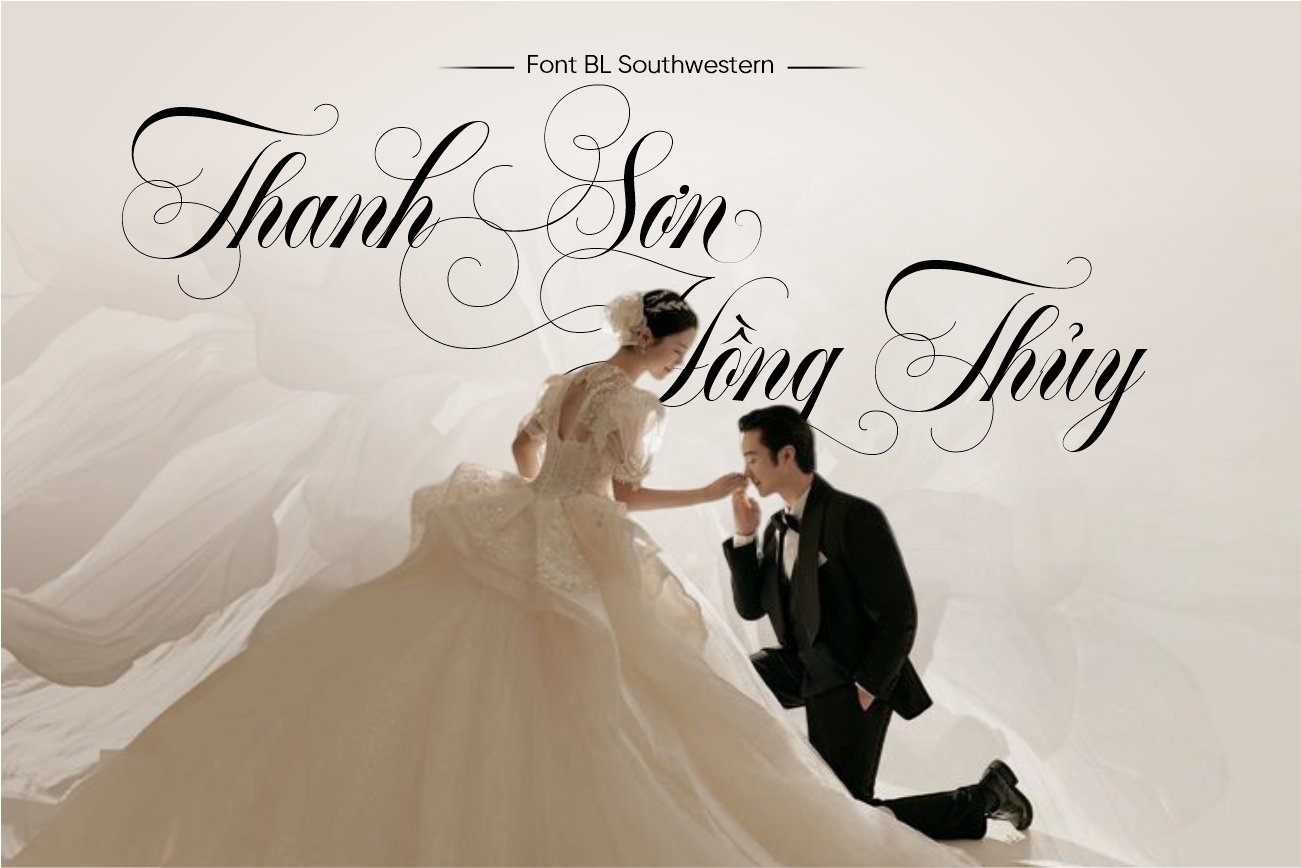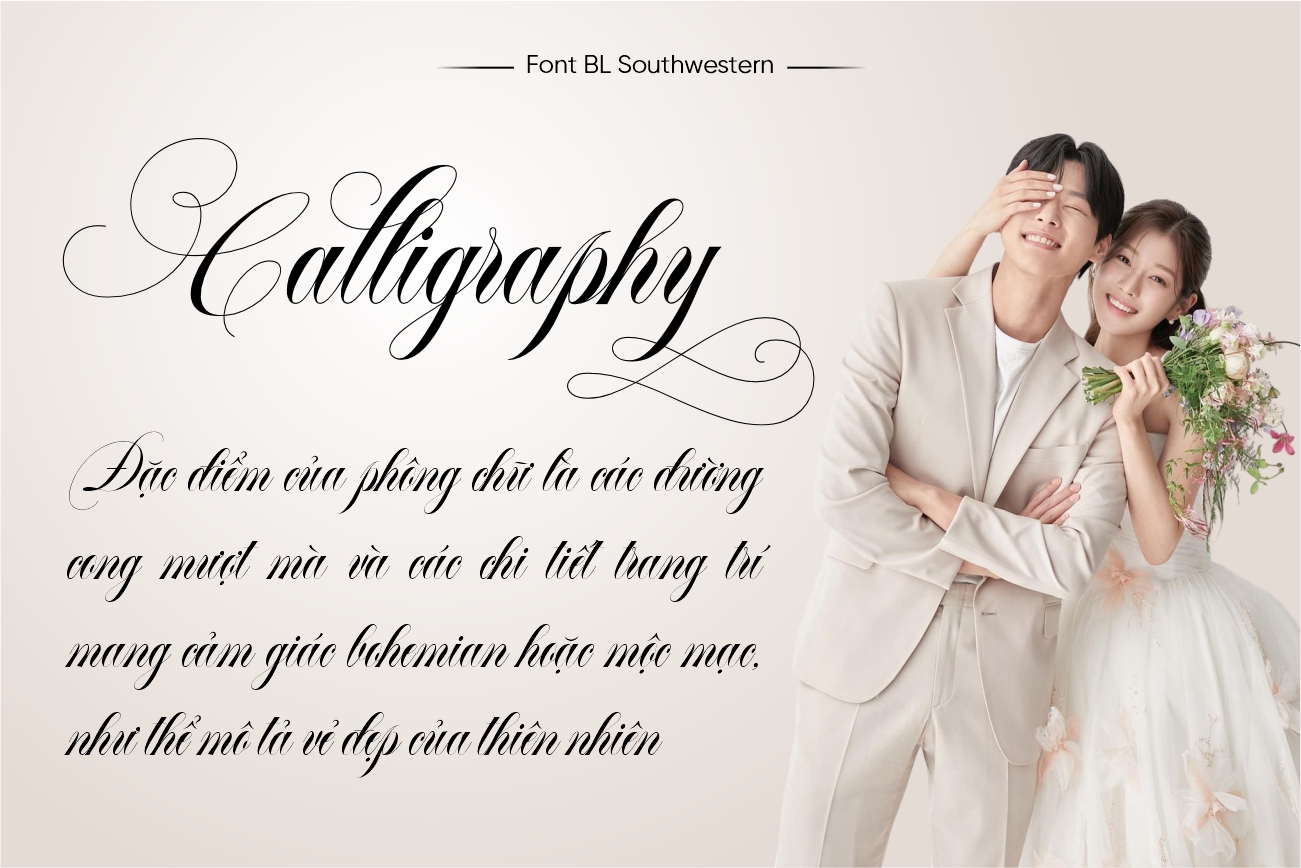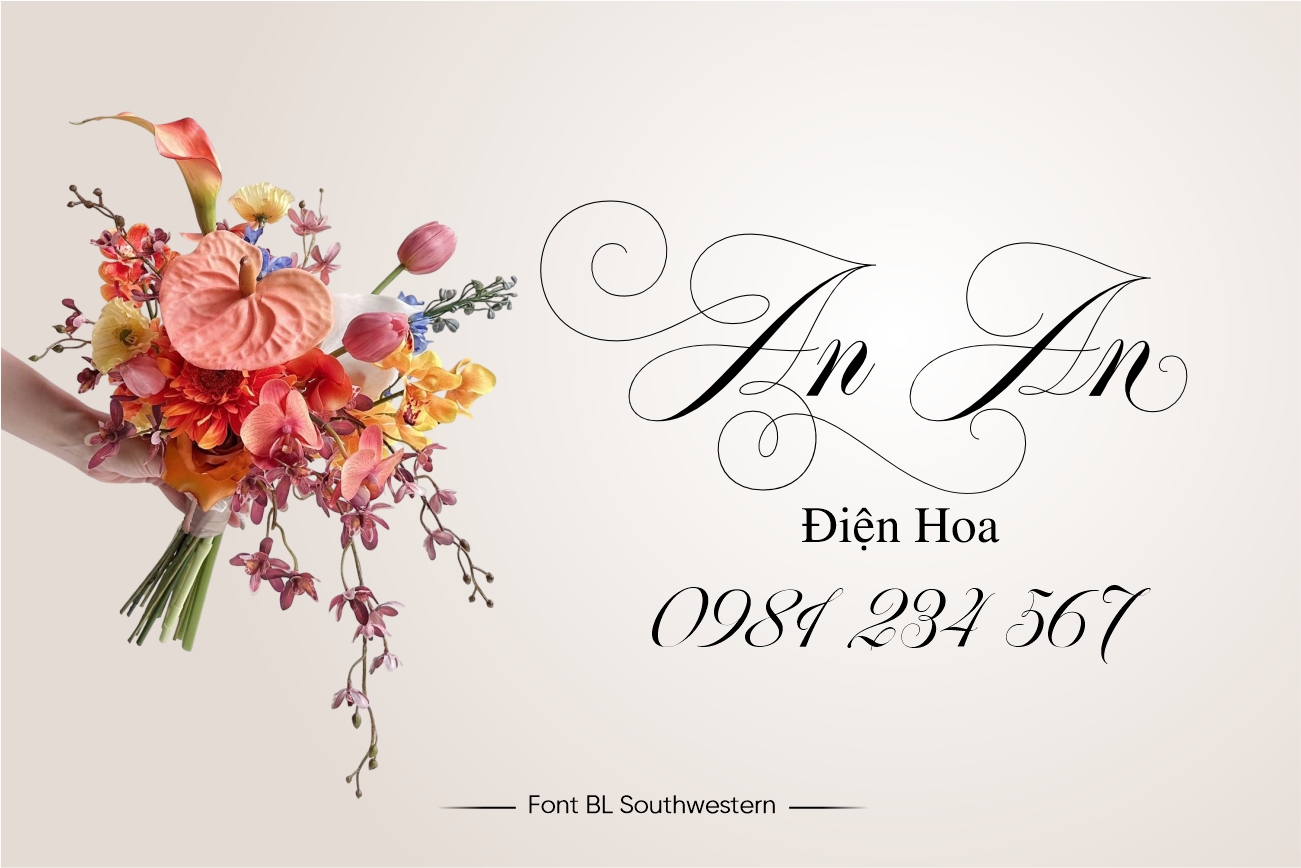
BL Southwester - Phông chữ thiệp cưới thanh lịch và nghệ thuật
BL Southwester là phiên bản Việt hóa của font chữ Southwestern do Suza Studio thiết kế, được Team BL tinh chỉnh để phù hợp hoàn toàn với hệ thống tiếng Việt. Nguyên bản Southwestern mang tinh thần tự do, phóng khoáng và giàu cảm hứng nghệ thuật, lấy cảm hứng từ những giá trị thủ công và vẻ đẹp cổ điển pha lẫn hơi thở đương đại. Sau quá trình Việt hóa, BL Southwestern vẫn giữ được cá tính riêng của thiết kế gốc, đồng thời được tối ưu về dấu và khoảng cách ký tự, đảm bảo hiển thị mượt mà trong các ấn phẩm in ấn và kỹ thuật số.
Về kiểu dáng, BL Southwestern nổi bật với những đường nét mềm mại, có độ cong uyển chuyển nhưng vẫn giữ được cấu trúc rõ ràng. Các ký tự được xây dựng theo phong cách thanh lịch và nghệ thuật, thể hiện sự chăm chút trong từng chi tiết nhỏ. Sự kết hợp các yếu tố truyền thống với nét hiện đại giúp font không chỉ mang dáng vẻ hoài niệm mà còn phù hợp với xu hướng thiết kế ngày nay. Nhờ cách xử lý hình khối hài hòa, font dễ dàng tạo điểm nhấn thị giác mà không làm mất đi sự cân đối của bố cục tổng thể.
Một điểm đặc biệt của BL Southwestern là khả năng tạo cảm giác tự nhiên và hữu cơ cho từng chữ cái. Các nét chữ không quá cứng nhắc mà có độ chuyển động mềm, gợi cảm giác như được viết tay một cách tinh tế. Điều này giúp font trở nên gần gũi và giàu cảm xúc hơn khi sử dụng trong các thiết kế như thiệp mời, bìa sách, poster nghệ thuật, bao bì thủ công hay logo thương hiệu mang tính cá nhân. Khi đặt trong bố cục dài, font vẫn giữ được sự rõ ràng và nhịp điệu ổn định, mang lại trải nghiệm thị giác dễ chịu.
Xét về nguồn gốc, Southwestern là sản phẩm thể hiện rõ định hướng sáng tạo của Suza Studio trong việc dung hòa giá trị truyền thống với thẩm mỹ hiện đại. Qua bàn tay Việt hóa của Team BL, BL Southwestern được hoàn thiện để đáp ứng nhu cầu sử dụng tiếng Việt một cách chính xác và thẩm mỹ. Sự hòa quyện giữa phong cách thanh lịch và nghệ thuật cùng khả năng kết hợp các yếu tố truyền thống với nét hiện đại đã tạo nên một bộ font linh hoạt, có chiều sâu và dễ ứng dụng. Với khả năng tạo cảm giác tự nhiên và hữu cơ cho từng chữ cái, BL Southwestern là lựa chọn lý tưởng cho những dự án thiết kế đề cao tính thẩm mỹ và cảm xúc lâu dài.